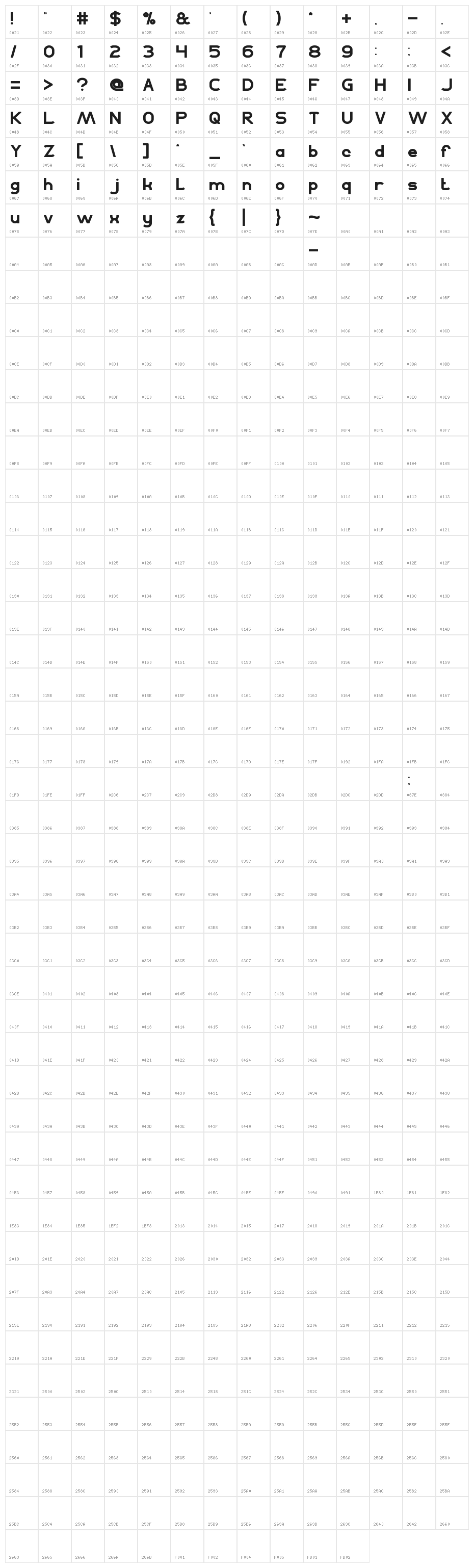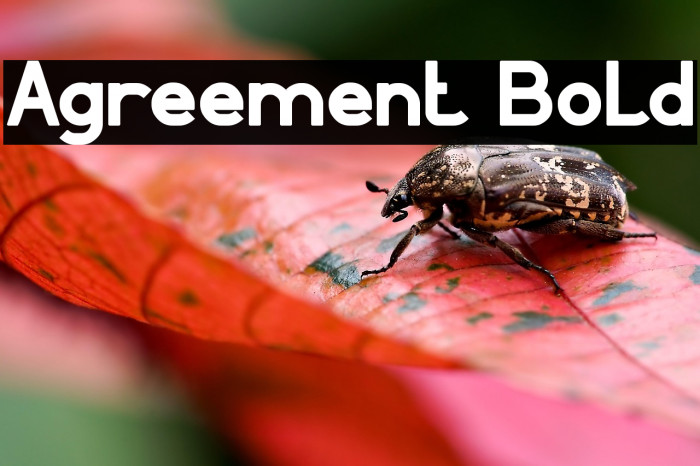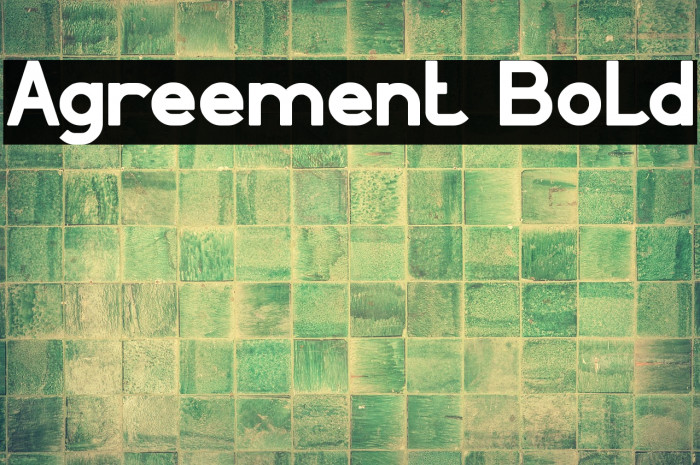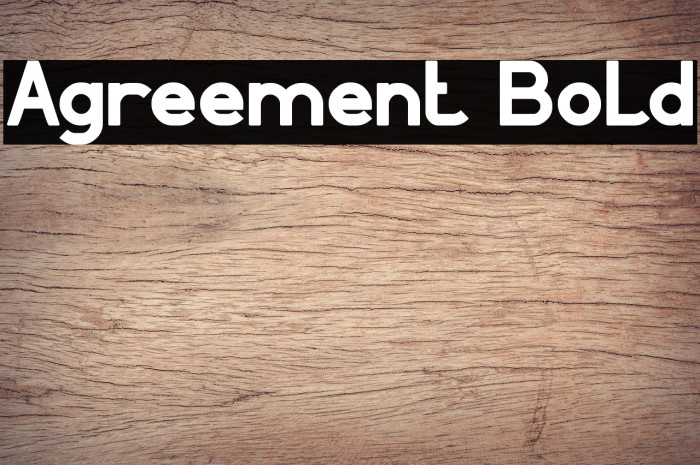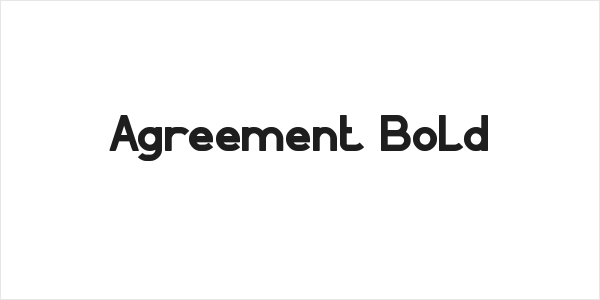
Agreement Bold Font
| उपयोग का मामला | Headlines, Logos, Posters |
| सुझाए गए प्रोजेक्ट | Ideal for branding, headlines, posters, and digital media where a strong, modern presence is desired. |